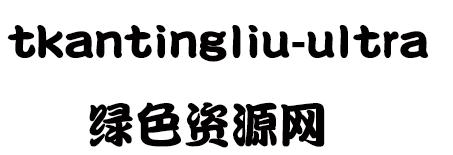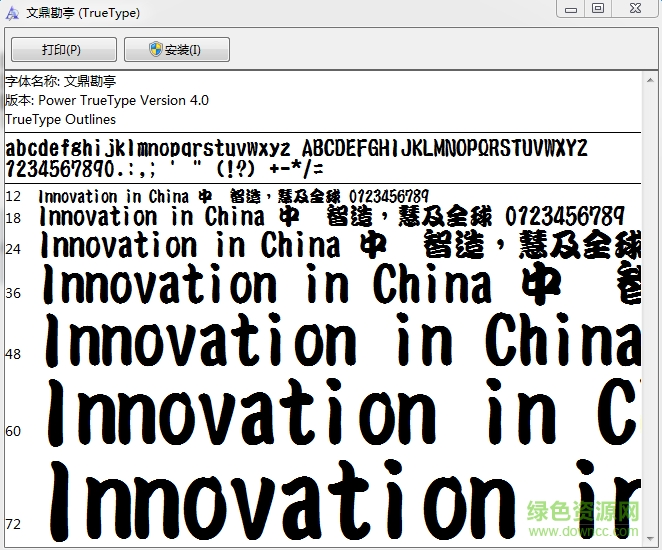
tkan tingliu ultra字體又叫文鼎勘亭流體,是一款風(fēng)格獨(dú)特的日式廣告字體,粗而不重,敦厚可親,新穎活潑,適用于宣傳標(biāo)題、歌舞廣告等領(lǐng)域,有需要者歡迎免費(fèi)下載
勘亭流體筆畫粗,字形圓潤(rùn)、敦厚,筆畫中極少出現(xiàn)直線與折角,幾乎全由曲線和彎角構(gòu)成,形成了其特有的藝術(shù)效果,倍受廣大平面設(shè)計(jì)者的青睞。